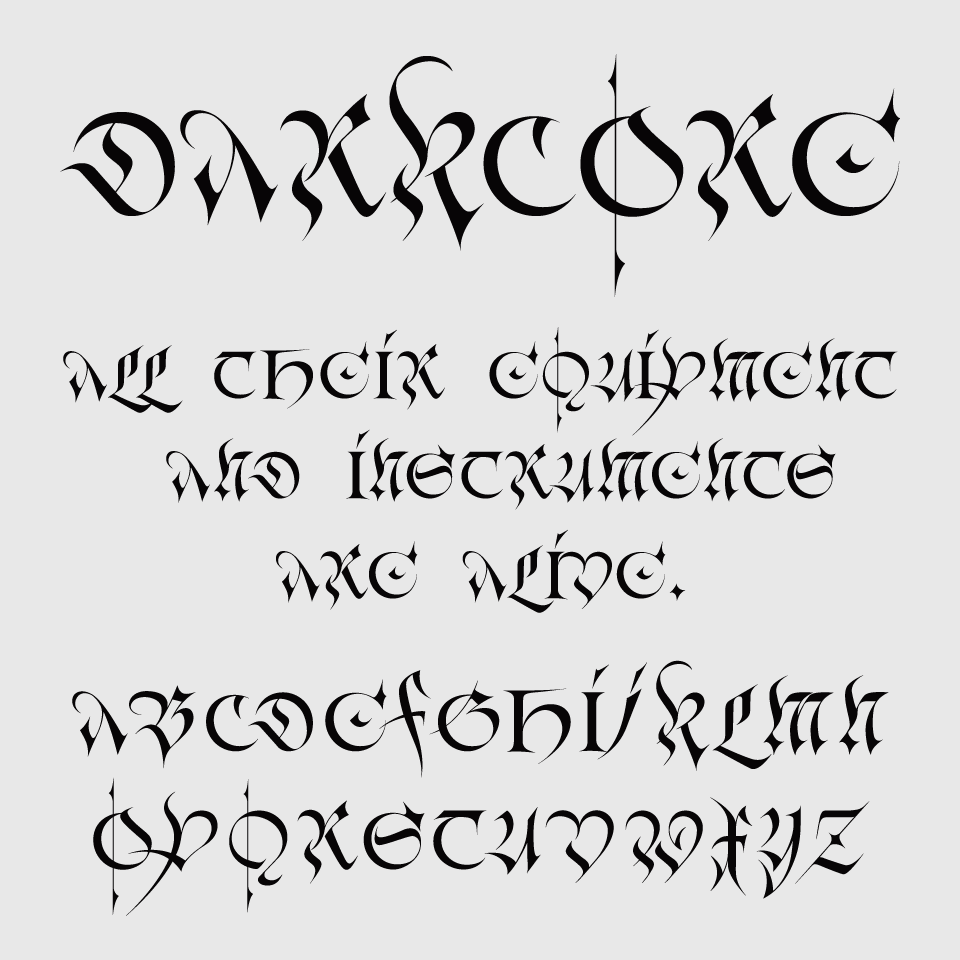
Darkcoreフォントは、鋭角で装飾的なゴシックスタイルが際立つ、強烈な個性を放つディスプレイフォントです。
文字の中にトゲのような意匠が施されており、ダークファンタジーやメタル系の世界観と相性抜群。禍々しさと神秘性のなかに、うっとりする美しくも危うい雰囲気が魅力なデザインです。
細部にまで徹底したデザインがなされており、キレイに文字組みするのが少し難しいですが、インパクトは極めて強く、使用する場面を選びますが、その分、世界観づくりに圧倒的な印象になること間違いなし!